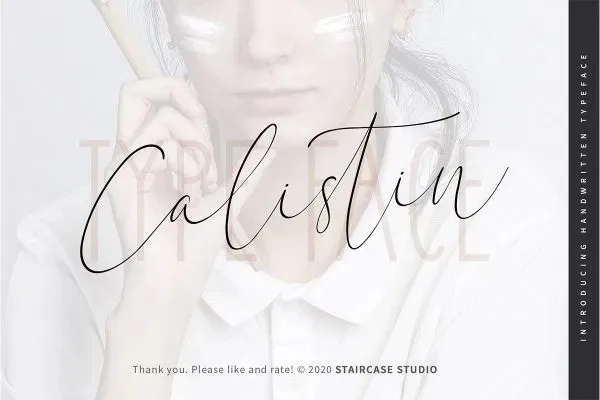
Calistin Font
A Calistin Font é uma elegante tipografia cursiva que se destaca por sua forma limpa e letras erguidas, garantindo sempre um toque descontraído. Esta fantasia do tipo foi meticulosamente criada para atender a necessidades variadas dos projetos de design. Perfeita para uso em logotipos, marcações e identificações, é também ideal para criar arte digital, letras para camisetas ou roupas, postais, folhetos, sinais e anúncios. Composta por letras e números adequados para seus trabalhos de design, a Calistin Font é um ótimo recurso para qualquer necessidade de design que você possa ter. Como uma fonte de escrita feita sob medida para designers em 99designs, ela promete tornar seu próximo projeto mais atrativo e sofisticado.